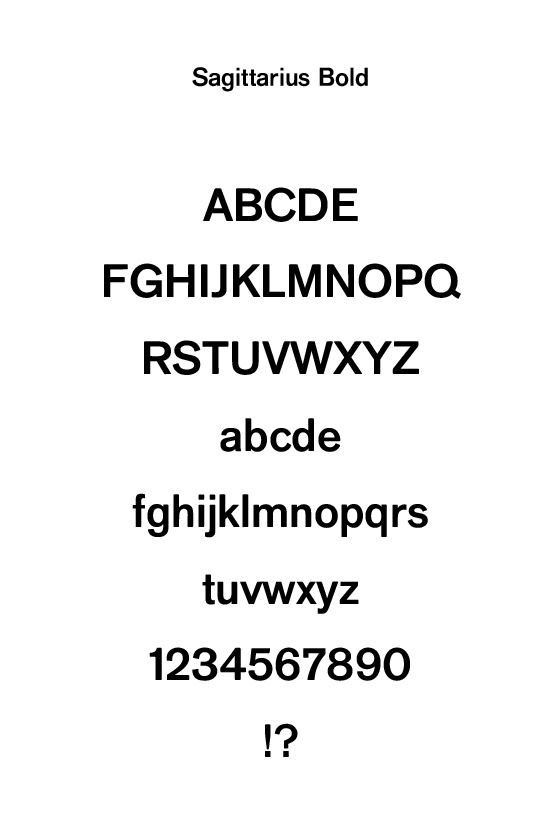
09A-1 欧字書体「K.E.Sagittarius-Bold」のよりどころ
原資料:『ノイエ・グラフィーク』(1958年)より
「アクチデンツ・グロテスク (Akzidenz Grotesk) 」は、1898年にドイツ・ベルリンのベルトルド活字鋳造所が製作した活字書体です。
そこで『ノイエ・グラフィーク』(1858年)所収の使用例から抽出したキャラクターなどをベースに、日本語組み版に調和するように制作しました。
活字書体 K.E.Sagittarius-Bold